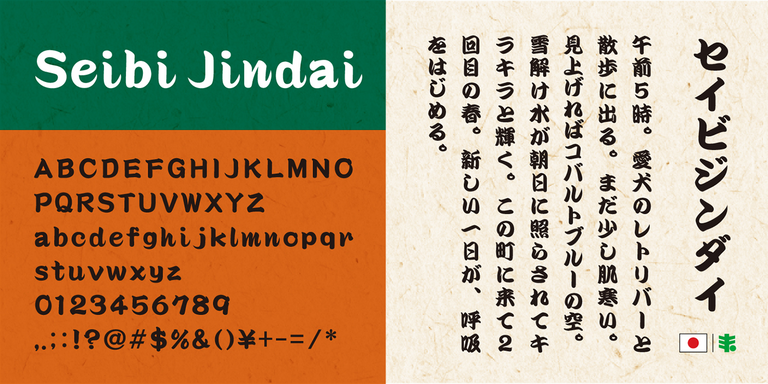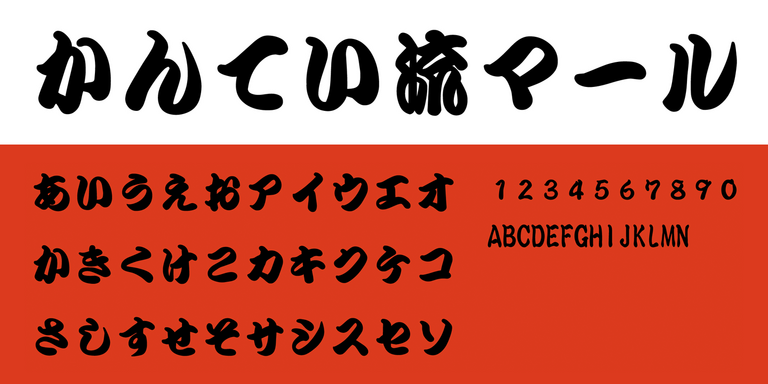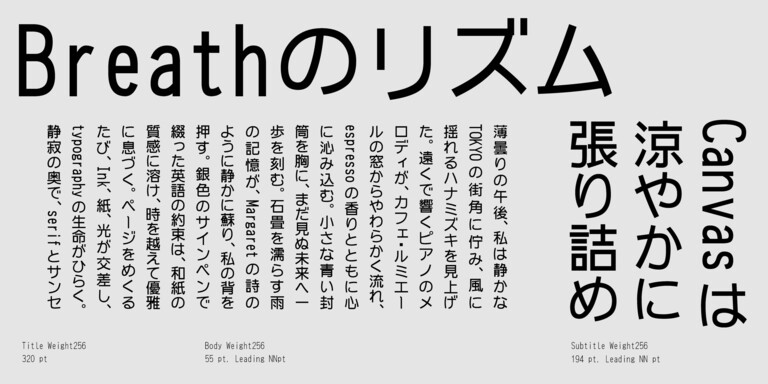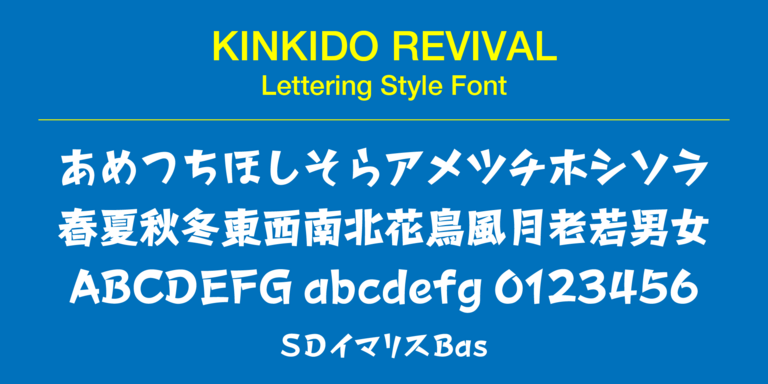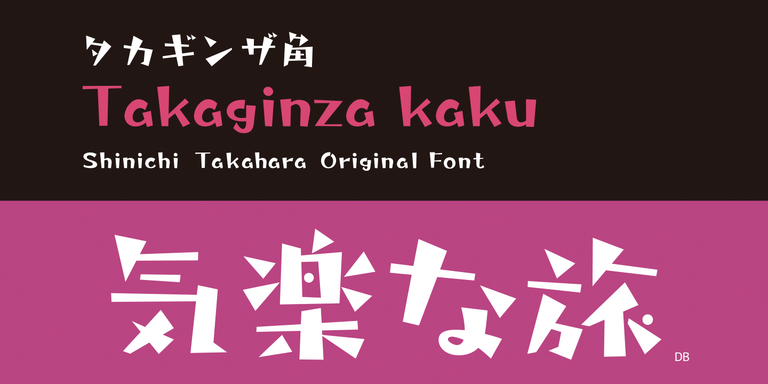
Monotype、フォントサービス LETS に国内書体メーカー 5 社の新書体 484 書体を追加
Monotype Fonts および LETS の書体ラインアップを拡充し、日本市場向けフォントソリューションをさらに強化
書体とフォント技術のグローバルリーダーである Monotype Imaging Inc.(本社:米国マサチューセッツ州ウォーバーン、CEO:ナイナン・チャコ(Ninan Chacko))はこのたび、日本市場向け個人・小規模事業者向けフォントサービス「LETS®」における提供書体に、日本の書体メーカー 5 社による新たな 484 書体を追加することを発表しました。これにより、LETS で利用可能な書体ラインアップをさらに拡充し、日本国内のユーザーへより幅広いタイポグラフィ表現を提供します。
今回追加されるのは、欣喜堂、マール社、リコーPFUコンピューティング、たかデザインプロダクション、および日本リテラルの各書体メーカーによる書体です。多彩なデザインスタイルとクリエイティブな表現を可能にする書体群が、LETS ライブラリへ新たに加わります。新書体は、2026 年 6 月 10 日より順次提供開始予定です。
また、これらの書体は、25 万書体以上を提供する Monotype® Fonts においても利用可能となります。これは、Monotype が推進するグローバルエンタープライズ戦略の一環として、日本市場およびグローバル市場に向けた企業向けフォントソリューションの拡充を進めるものです。
今回のライブラリ拡充は、日本市場への継続的な投資を示すものであり、国内のクリエイティブニーズやビジネスニーズに対応した高品質な書体と柔軟なフォントソリューションの提供をさらに強化するものです。
追加書体メーカー一覧
欣喜堂
欣喜堂は、有限会社今田欣一デザイン室が手掛けるファウンダリーになります。今回、「欣喜堂リバイバル」(KINKIDO REVIVAL)として、1997年から2000年までに制作したカスタムメイド書体の復活プロジェクトです。手書きフォント(Handwritten Style Fonts)は書写の基本である楷書体、行書体、隷書体をベースに、デザインフォント(Lettering Style Fonts)は近世の江戸文字風、近代の図案文字風、現代の企業制定文字風をベースにしています
マール社
マール社は美術・デザイン書、実用書、ビジュアル資料集などを発行している日本の出版社です。書籍で刊行していた広告用書体シリーズ「ディスプレイ書体シリーズ」「デザイン筆文字シリーズ」のうち、特に特徴ある書体をフォント化いたしました。楷書体や行書体、かんてい流や千社文字など多彩なラインナップをお楽しみ頂けます。
リコーPFUコンピューティング株式会社
リコーPFUコンピューティング株式会社は、MS 明朝、MS ゴシックを作ったフォントファウンダリーです。両書体は 1992 年に初めて Windows に搭載された日本語 TrueType Font で、その後さまざまな進化をしながら現在も Windows や Office ソフトの標準フォントとして使われています。HG の付く書体が目印です(HG 創英角ポップ体など)。
たかデザインプロダクション
タイプ作家:高原新一が「タカ 書体」として創作する個性豊かな書体です。
日本タイポグラフィ年鑑でのグランプリ受賞、ニューヨーク TDC 展入選、CS デザイン賞銀賞、各種書体コンテスト入賞、入選等多くの受賞歴をもつ。タイプデザイナー、タイポグラファーとして TV 等で紹介。これまでロゴタイプ、シンボルマーク等、CI、VI を制作。絵文字作品は中学教科書に掲載。
日本リテラル株式会社
日本リテラル株式会社は、出版社や新聞社の書籍広告における見出し用文字の制作に携わってきました。
木版やレタリングの伝統を背景に、活字や写植にないデザインを求めるお客様の要望に応えて誕生した独自の書体ブランド、それが「セイビフォント」です。
Q. どの書体メーカーの書体が追加されますか?
A. 欣喜堂 、マール社、リコーPFUコンピューティング、たかデザインプロダクション 、および日本リテラルの書体が追加されます。
Q. 今回の書体追加の特徴は何ですか?
A. 国内書体メーカーによる多彩なデザインスタイルや表現力豊かな書体が追加されることで、LETSで利用可能な書体バリエーションが大幅に拡充されます。